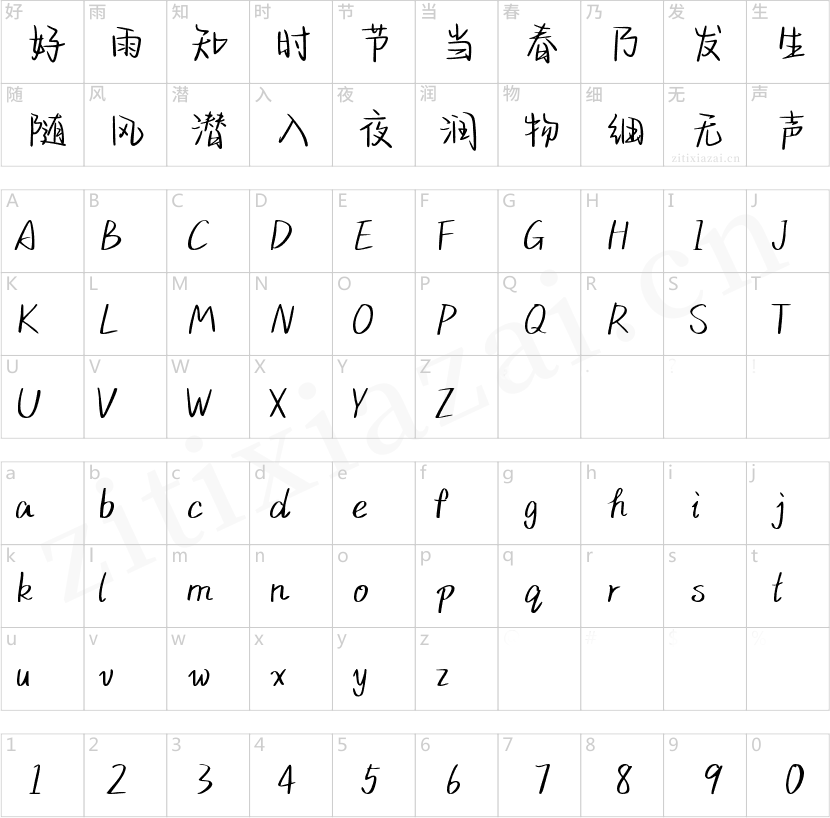
Aa魔法宇宙砂糖星云
Aa魔法宇宙砂糖星云字体
Aa魔法宇宙砂糖星云是一款非常具有艺术性的字体,它的设计灵感来源于对古典艺术的研究,同时又融入了现代字体设计的元素。字形优美,笔画粗细变化自然,给人以大气、典雅的感觉。Aa魔法宇宙砂糖星云是一款既传统又现代的字体,它的设计充满艺术感,美观大方,实用性也非常强。无论是对于设计师还是对于普通读者来说,都是一种非常不错的字体选择。Aa魔法宇宙砂糖星云适合用于具有艺术感的场合,比如海报、宣传单张、书籍封面等。由于其字形流畅且具有动态感,也适合用于大量的文本排版,如报纸、杂志等。